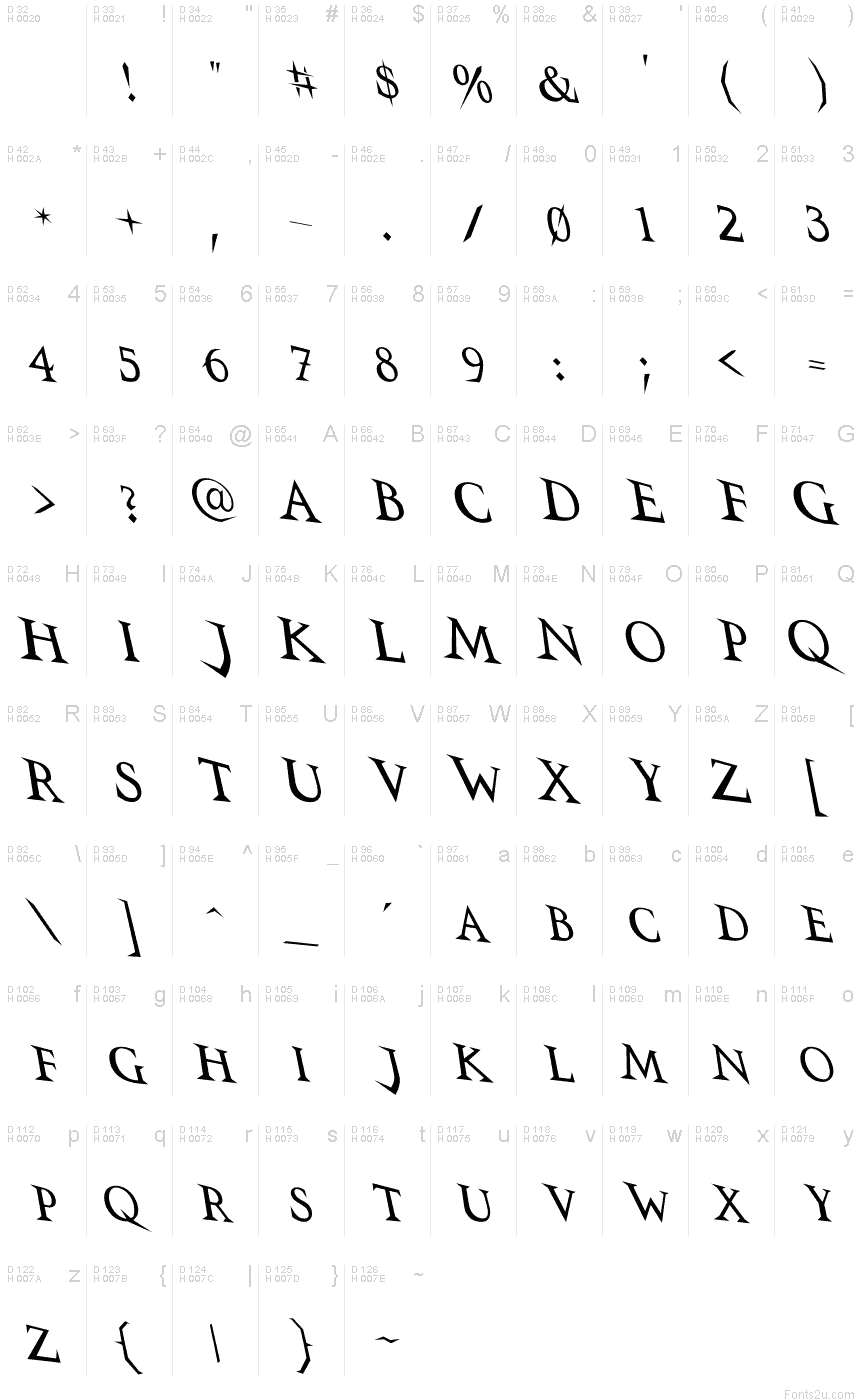
Podgląd czcionki VTCSwitchbladeRomanceDrunk
VTC Switchblade Romance Drunk od V.T.C. Vigilante Typeface Corporation to darmowy, zniekształcony krój szeryfowy typu display z ostrą, nocną estetyką pulp. Litery pochylają się i chwieją, mają zakończenia przypominające kliny i łączą eleganckie, klasyczne krzywizny z celowo surowym, nierównym rytmem, który wydaje się nieco niebezpieczny i teatralny.
Sprawia to, że ten darmowy font jest naturalnym wyborem na plakaty horrorów, okładki zinów, ulotki zespołów, branding inspirowany tatuażami czy plansze tytułowe, gdzie ostre szeryfowe kształty potrafią zdziałać więcej niż zwykłe liternictwo. Sprawdza się również w krótkich nagłówkach i klimatycznych monogramach, zwłaszcza gdy szukasz czegoś, co na pierwszy rzut oka wygląda romantycznie, a na drugi – drapieżnie.